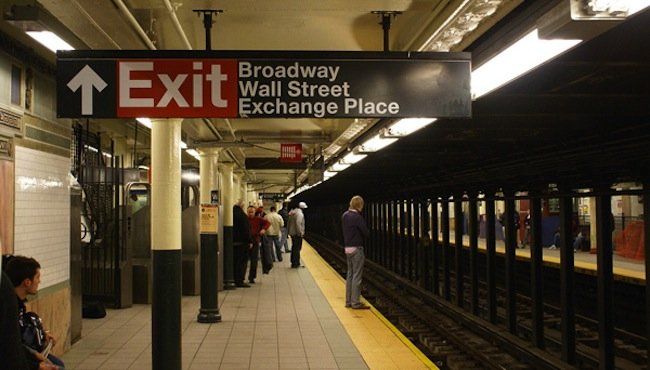
Helvetica, historia de cómo una tipografí­a cambió el mundo
En nuestro ajetreado dí­a a dí­a no solemos pararnos a pensar en las cosas que nos rodean, como por ejemplo, la tipografí­a en la que están escritos los carteles, cajas de medicamentos, señalizaciones de la calle, etc. Muchas de estas cosas están escritas en un tipo de fuente llamada Helvetica, también conocida antaño como Neue Haas Grotesk, y es la bella más bella de entre todas las tipografí­as para millones de personas y diseñadores gráficos de todo el mundo. Digamos que la antí­tesis de la horrible Comic Sans, pero ¿por qué?
Helvetica es un interesante documental sobre la propia existencia de esta fuente tipográfica y por qué a dí­a de hoy es un elemento tan adorado en todo el mundo, principalmente por diseñadores gráficos. Nunca algo tan sencillo y complejo a la vez pudo ser objeto de alabanza y desprestigio al mismo tiempo.
En algo más de hora y media de duración, el documental desgrana los secretos de la tipografí­a y cómo ha conseguido convertirse en un tótem de la comunicación a nivel mundial. Su concepción, la ideologí­a que hay detrás de Helvética y la historia de la misma son algunos de los pilares del documental.
¿Cómo influye una tipografí­a en nuestra vida?
«Helvetica» es ante todo, un documental curioso. Percibir el mundo puede parecer una tarea sencilla cuando realmente es una de las tareas más complejas que existen. Disponer de un recurso técnico capaz de comunicar algo positivo y/o negativo al mismo tiempo y sin ser modificado, requiere una meticulosa concepción.
En el documental, todo está basado en entrevistas con importantes diseñadores gráficos alrededor del mundo y constantes ejemplos de utilización cotidiana en las calles, carteles, señalética de estaciones de metro, edificios, que explican la capacidad comunicativa de Helvetica y su éxito mundial.
Fue en los años 60 cuando esta tipografí­a, creada en Suiza por Max Miedinger, comenzó a convertirse en extremadamente popular. Quizás su estilo y el buen trato que ha tenido por parte de los diseñadores con el paso del tiempo han sido factores clave para situarla en la escala en la que se encuentra a dí­a de hoy, aunque también influyó la gran reputación que tení­a el diseño suizo a nivel global por aquella época.
Resulta impactante ver cómo la terminación de una letra «a» puede variar el significado y forma de una palabra. Es en el detalle donde está la diferencia.
Es por eso que es un documental para los amantes del diseño gráfico y diseño en general. La cinta no es nueva, se produjo hace varios años por el director Grey Hustwit y no es un producto para el público masivo.